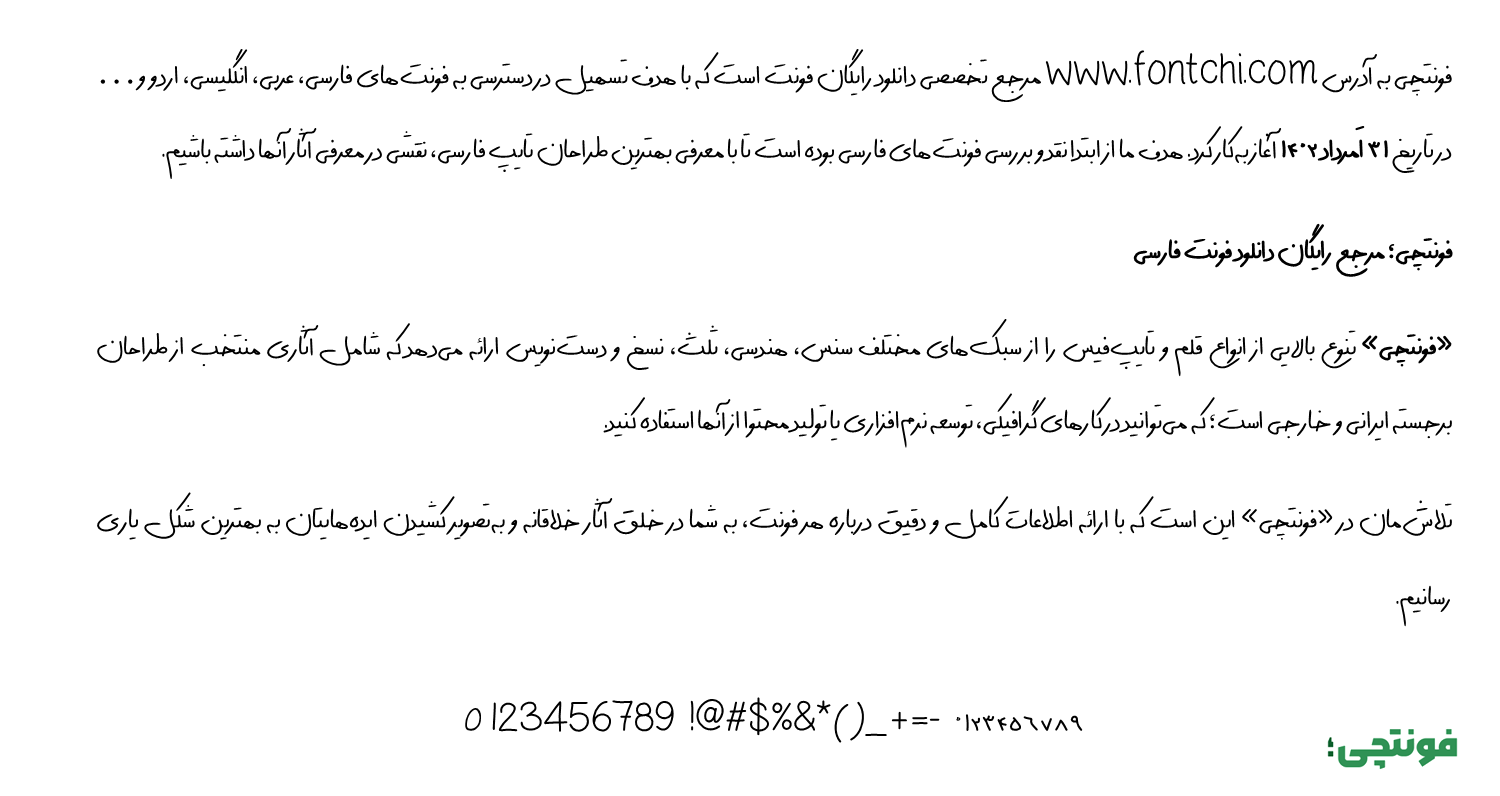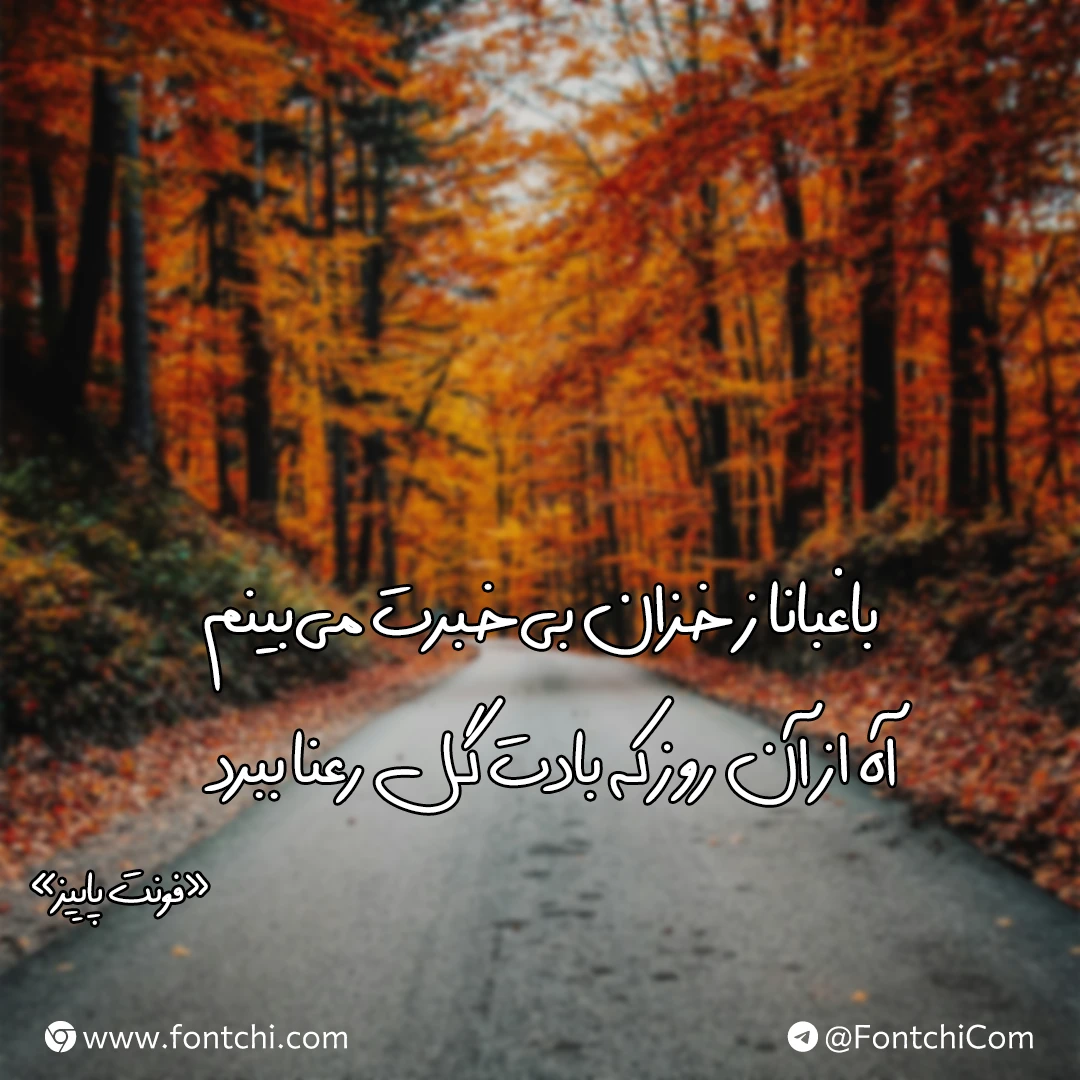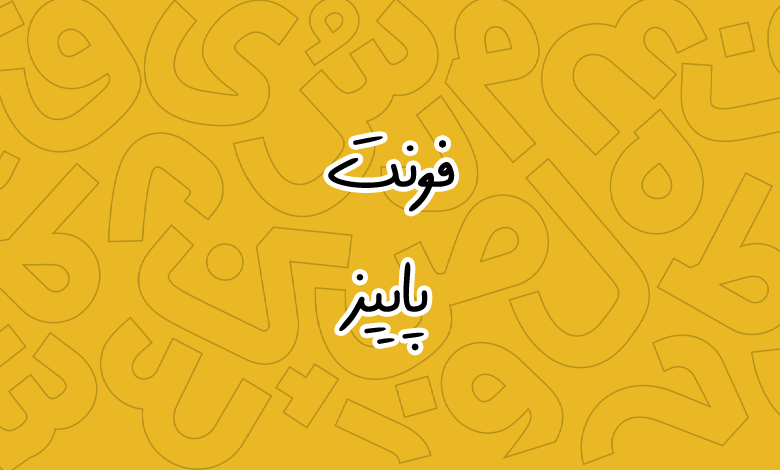
فونت پاییز (Paeez)
فونت پاییز (به انگلیسی: Paeez) قلمی دست نویس با ظاهری فانتزی است که میتوانید از آن در کارهای گرافیکی و تولید محتوای شبکههای اجتماعی استفاده کنید. این فونت از هر سه زبان فارسی، عربی و انگلیسی پشتیبانی میکند که در ادامه با دانلود فونت پاییز با شما همراه هستیم.
فونت پاییز توسط مهدی برقگیر طراحی شده است. قلمی با ضخامت نسبتا نازک که از سبک نقطهگذاری پیوسته برخوردار است. در این فونت هر حروف دارای کشیدگیهای خود هستند و از قانون یکسانی تبعیت نمیکنند.
در فونت فارسی پاییز که از زبان عربی و انگلیسی هم پشتیبانی میکند، تقریبا تمامی گلیفها با ظاهر استاندارد خود طراحی شدهاند. جز برخی حروف عربی مانند «ي» که بهجای آن از «ئ» استفاده شده است. در بخش اعداد نیز شاهد استفاده از عدد عربی «٥٦» برای زبان فارسی هستیم. در مقابل برای زبان عربی نیز از عدد فارسی «۴» استفاده شده است.
فونت paeez انگلیسی نیز دارای همین سبک طراحی است اما یک ایراد جزئی برای زبان لاتین اندازه بزرگتر گلیفها است که در صورت استفاده از هر دو زبان، شاید نیاز باشد اندازه حروف انگلیسی را نسبت به فارسی کمی کوچکتر کنید. در بخش کاراکترهای خاص نیز برخی کاراکترها فاقد گلیف هستند.
از فونت پاییز میتوانید در هر جایی که نیاز به فونت دست نویس دارید استفاده کنید. این فونت دست نویس فارسی دارای ظاهر نمایشی است که میتواند نگاه مخاطب را به خود جذب کند. حروفی مانند «ع، ن، ل، ی، م، ق» در بخش منحنی خو دارای کشیدگی و ابعاد بزرگتری هستند که ظاهر فونت را نمایشی میکند. همچنین این فونت از گلیف «تومان» برای درج قیمت نیز پشتیبانی میکند.